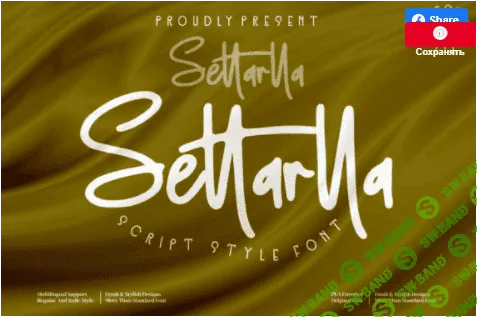
Название: Settarlla Font (2022)
[creativefabrica] Settarlla Font (2022)
Settarlla - это великолепный шрифт, подходящий для любых проектов, таких как логотипы, брендинговые проекты, дизайн товаров для дома, упаковка продуктов, кружки, цитаты, плакаты, сумки для покупок, футболки, обложки книг, визитные карточки, пригласительные билеты, поздравительные открытки, этикетки , фотографии, водяные знаки, специальные мероприятия и все другие ваши роскошные проекты, которым нужен фирменный вкус премиум-класса.